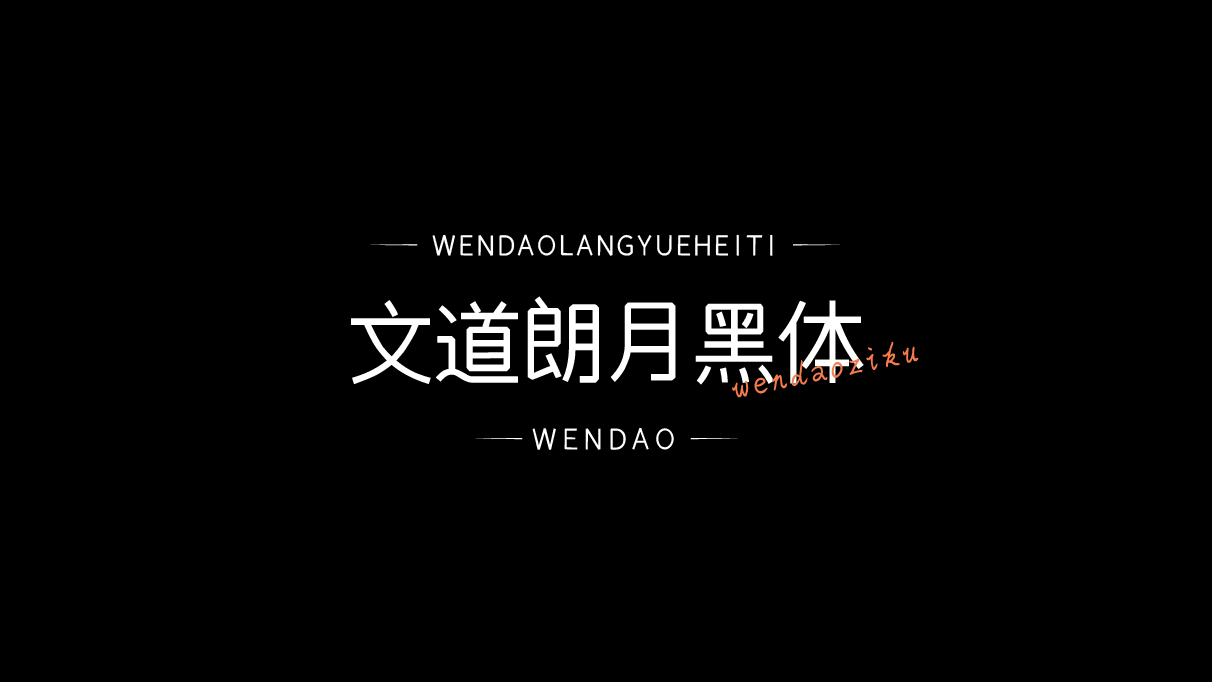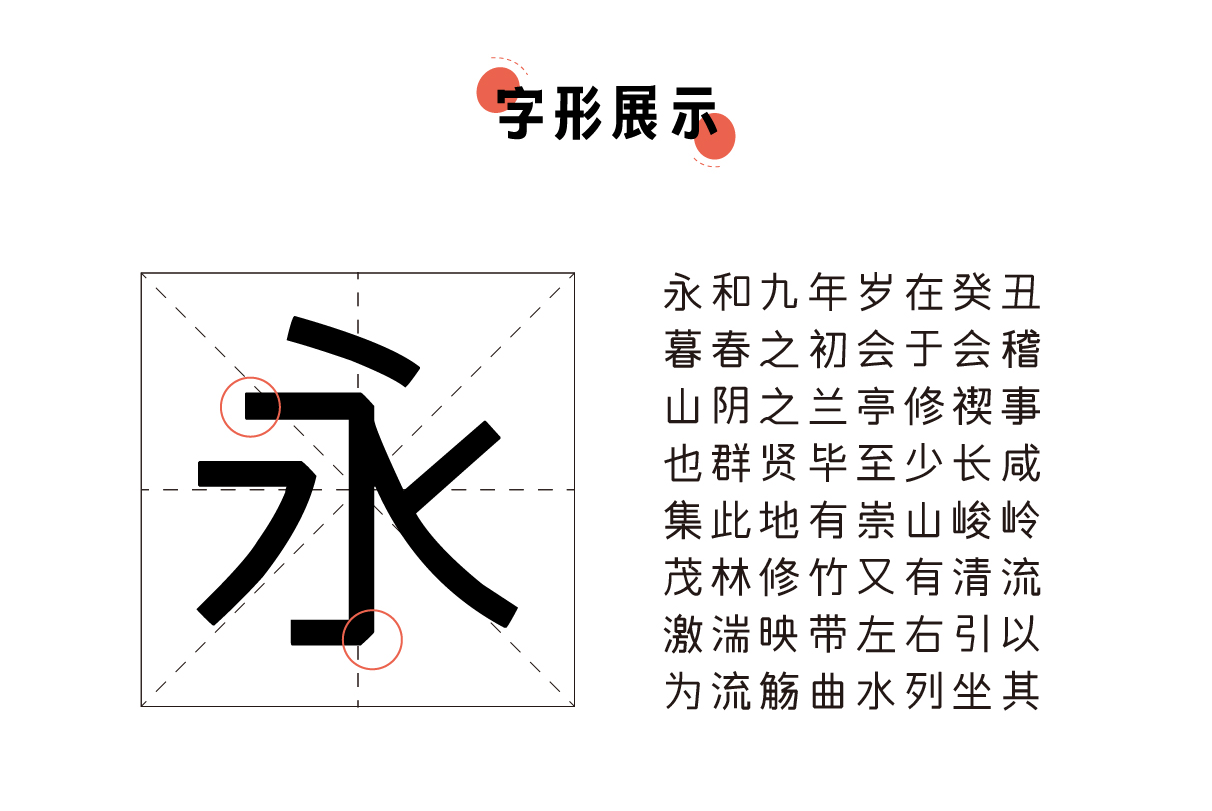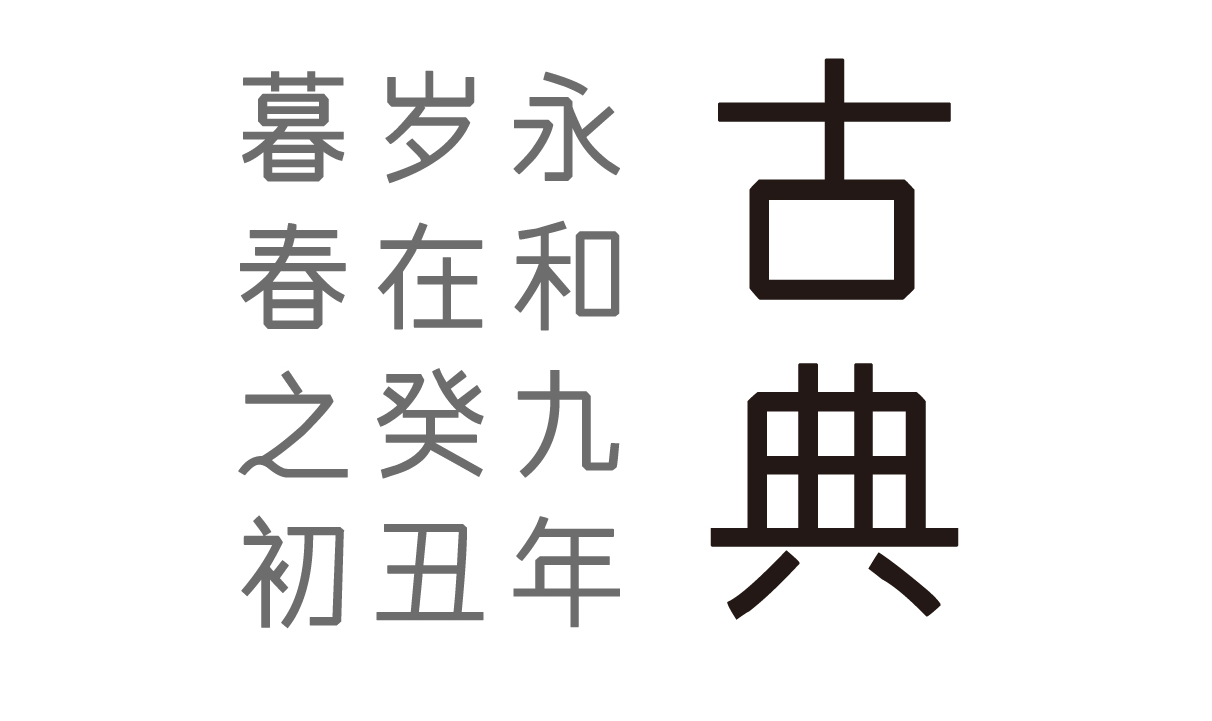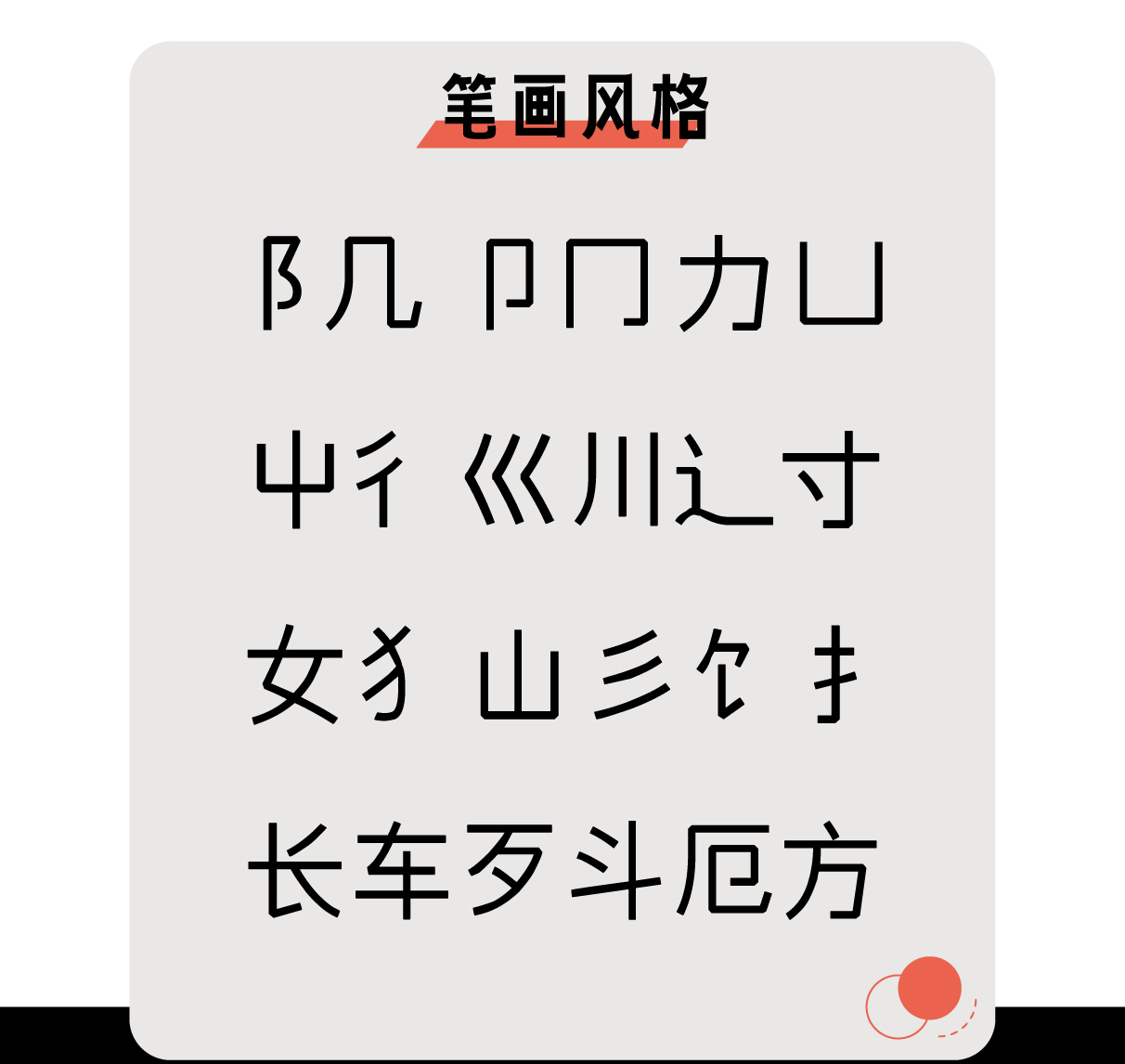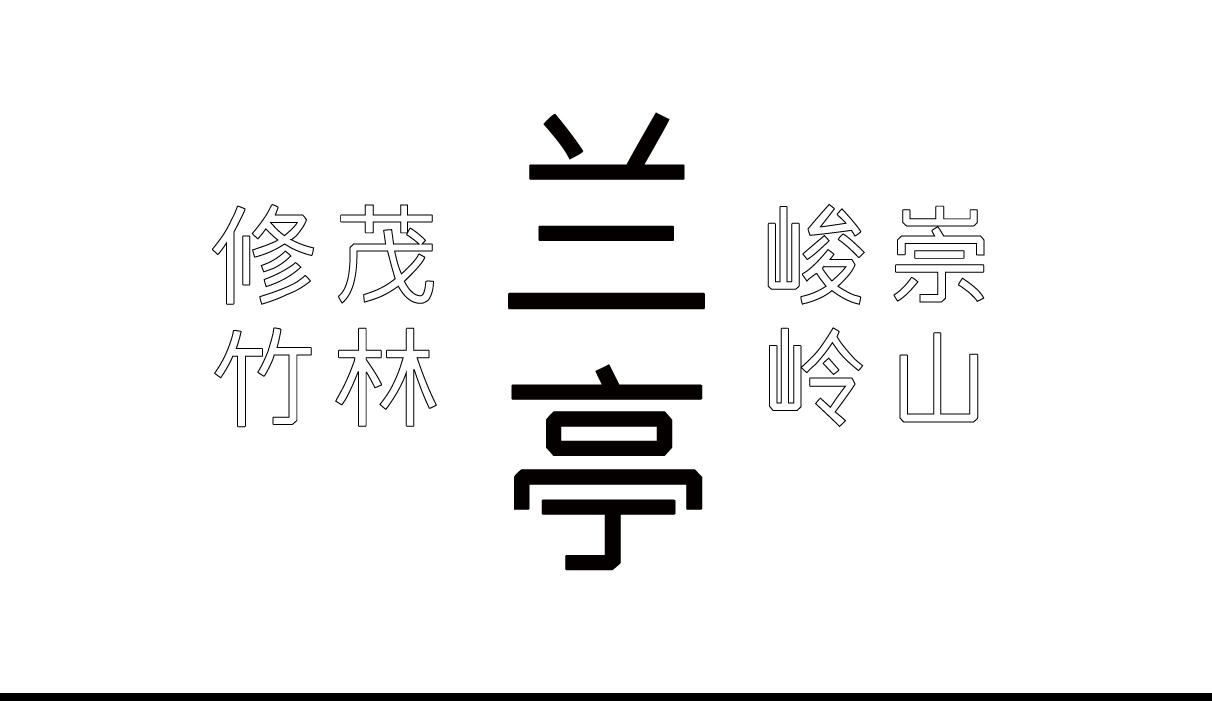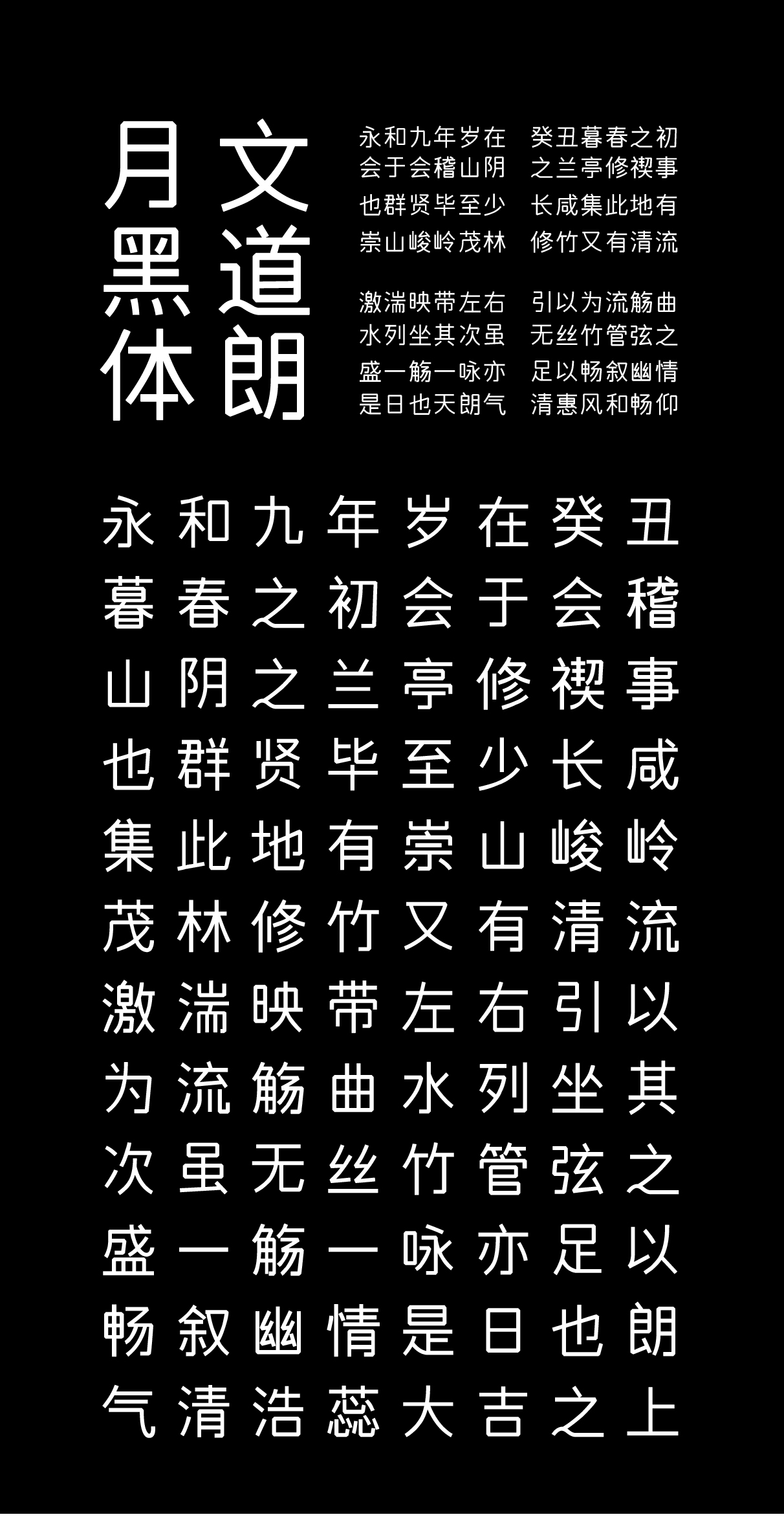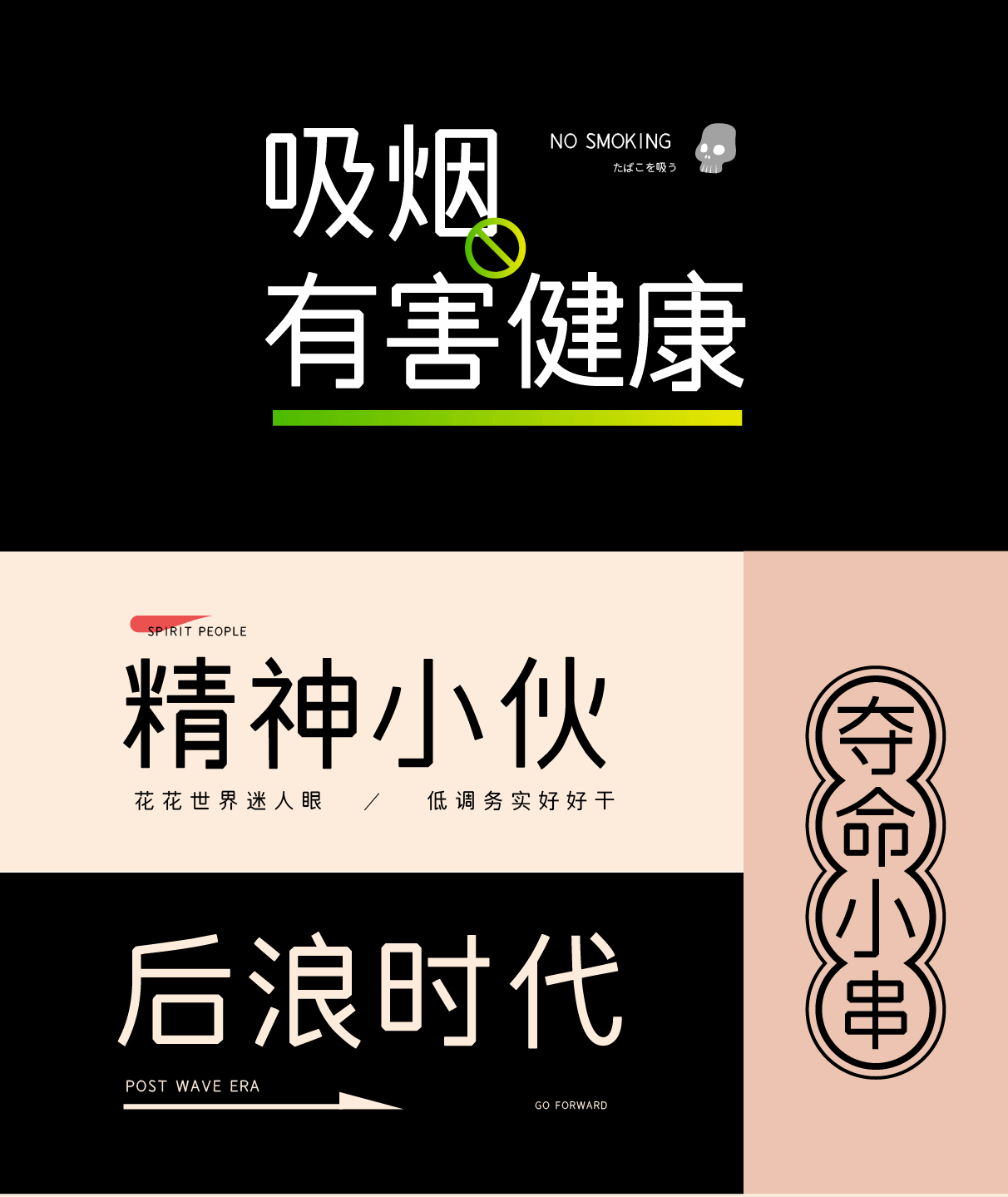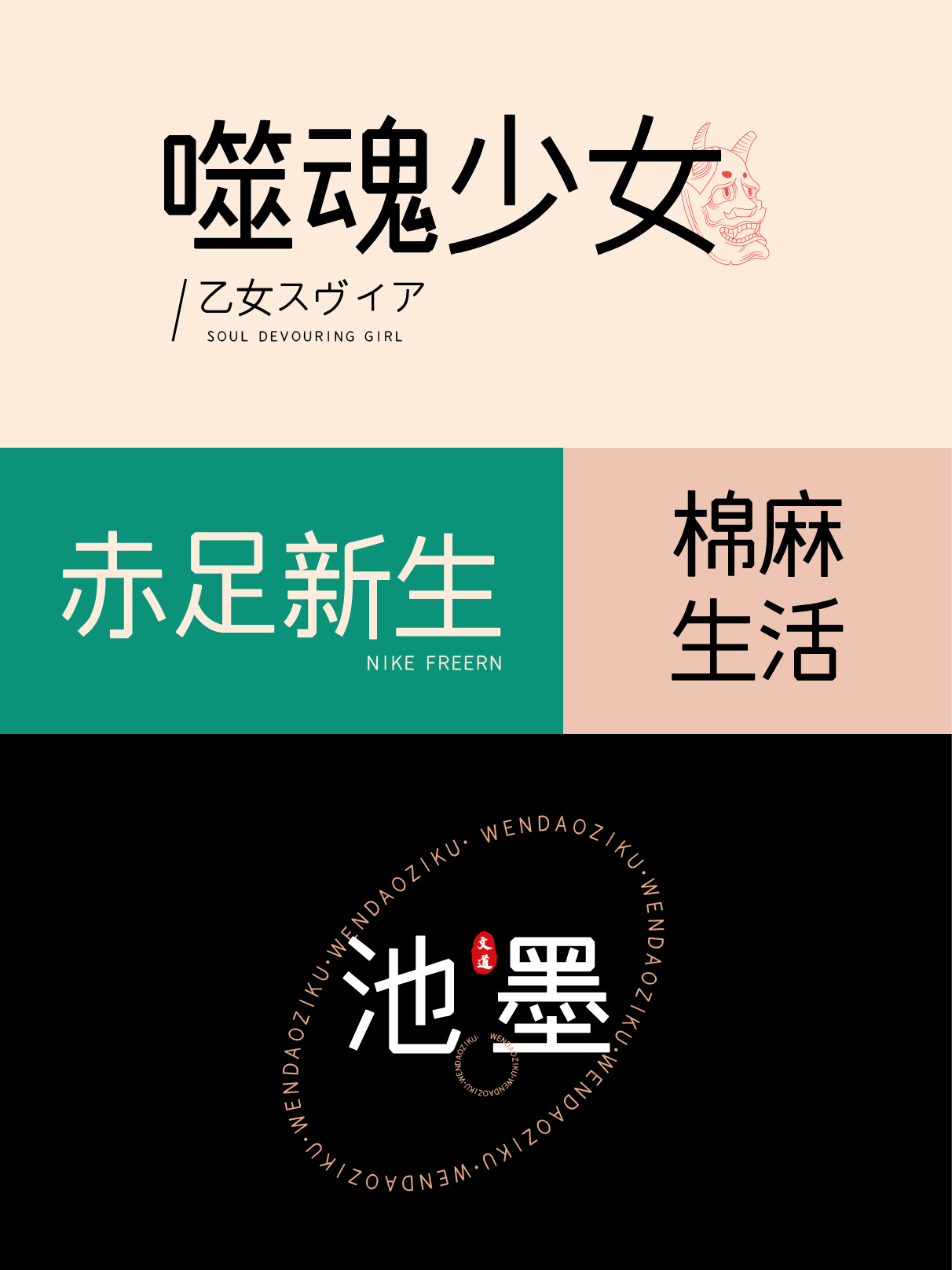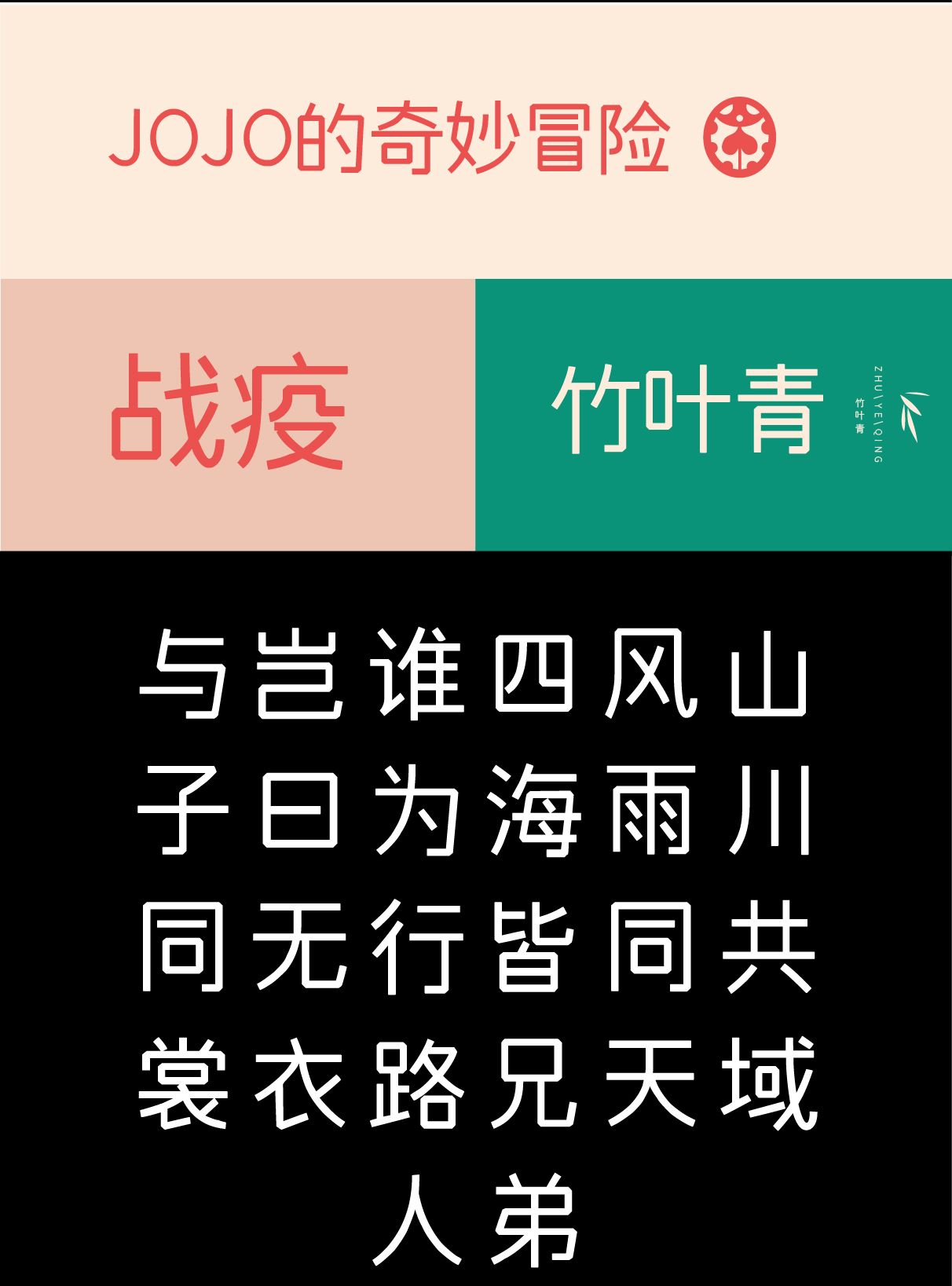
| 字体名称: | 文道朗月黑 |
| 所属分类: | 黑体 屏显 |
| 简介: | 文道朗月黑的字形结构源于传统黑体,为单个设计师独立完成,字面大小及笔画粗细得到整体的协调。 设计师此款设计笔画进行镜像对称处理,将所有钩笔和折笔部分加入轻微切角。 文道朗月黑的字形风格清朗有力,字形欣长又中和内敛,追求字体整体和谐,除了满足传统印刷媒介的各类标题,还适用于屏幕显示、广告标语和包装设计 |